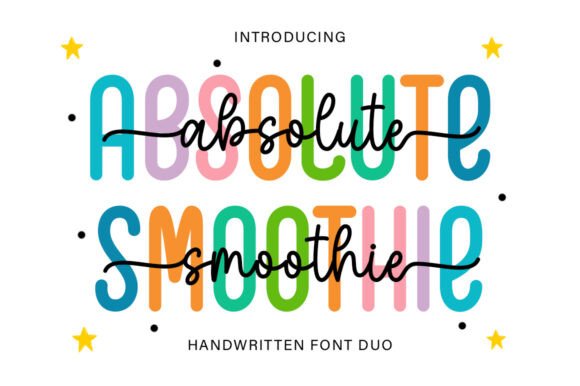
Absolute Smoothie Duo
找到合适的设计元素可能具有挑战性,但 Absolute Smoothie Duo 提供了一系列出色的藏品,可瞬间提升您的作品质量。
无论您是创建 POD(按需打印)产品、婚礼邀请函还是社交媒体图形,Absolute Smoothie Duo 都是理想的选择。